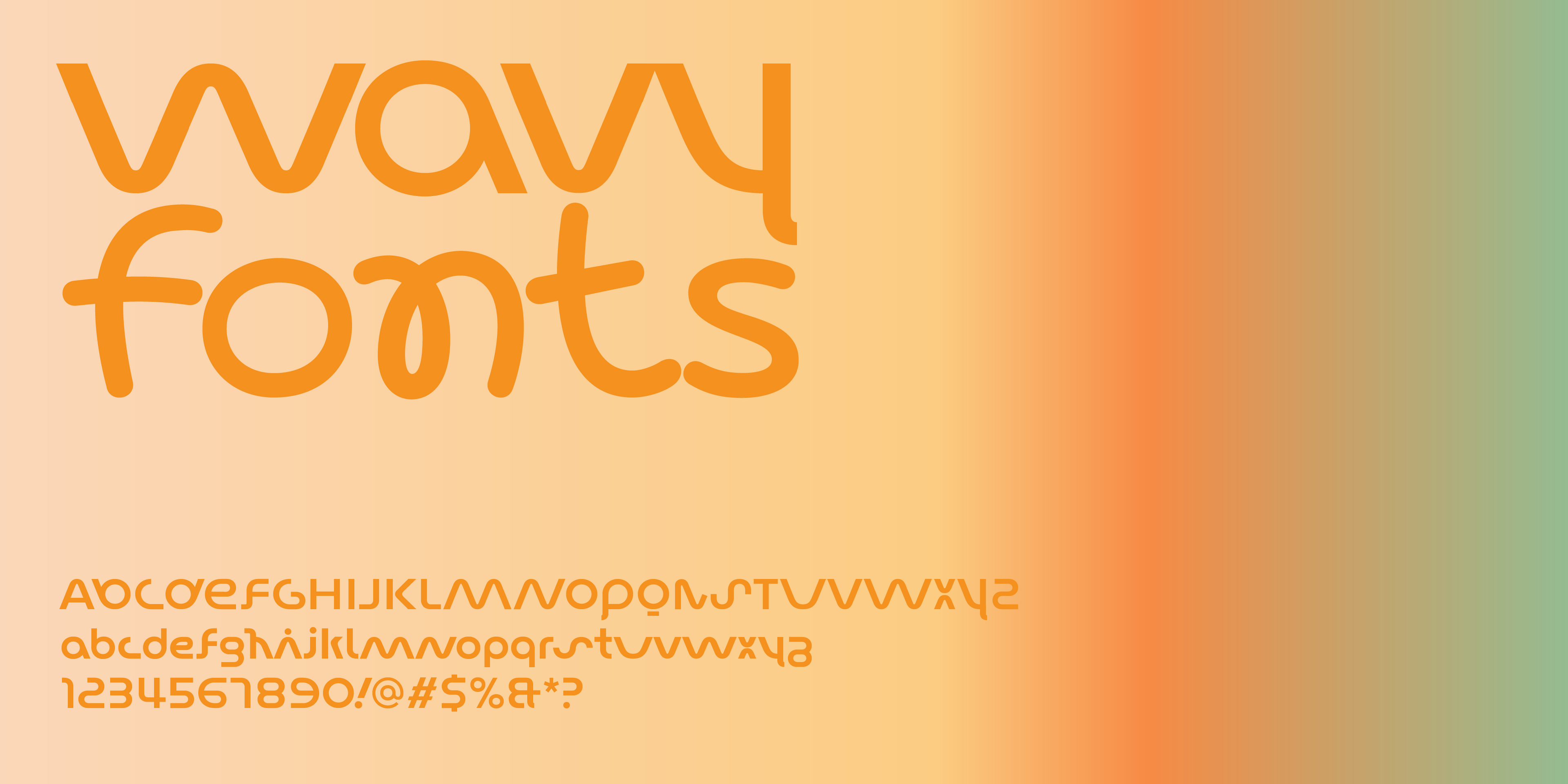
Las fuentes onduladas aportan una personalidad divertida a los diseños de logotipos y titulares. Ya sea que estés buscando una tipografía con un contorno ondulado general o una cuyas letras recreen un diseño similar a una onda de sonido, en este artículo, veremos ocho fuentes onduladas que aportan un carácter alegre y fresco a cualquier texto.
Tipografías divertidas y modernas
Esta primera tipografía, Lace Regular , es una fuente monolineal (los trazos tienen el mismo grosor) que se asemeja a una cuerda o cinta suave. Es una fuente agradable que se adapta perfectamente a los diseños de verano, con barras deformadas y terminales ondeando con el viento (compare el trazo horizontal de la letra f y el terminal de la letra r).
Skay, en grosores muy llamativos como Black, es una fuente ideal para logotipos con estilo. Skims utiliza una fuente similar , aunque su objetivo de comunicación es presumiblemente algo así como "formas corporales más suaves y redondeadas". Combinada con una paleta de colores cálida y apagada, crea un aspecto retro a través de su diseño de pincel suave y fluido. La tipografía se siente suave y burbujeante debido a su redondez hinchada, dinámica debido a sus ejes de letras irregulares y adaptable a cualquier espacio debido a su variabilidad de trazos de letras.
Kijs es una de mis fuentes favoritas para usar en estos días debido a su versatilidad. Esta fuente viene con letras alternativas que son más "estilo pincel" y, además, con glifos serif regulares que puedes intercambiar con los valores predeterminados más orgánicos. Si bien puede que no tenga un diseño de tipografía ondulada innata, configurar el texto en Kijs Bold (o más negrita) crea una apariencia natural y curva. La razón de eso es que algunas de las letras están en cursiva y otras letras están diseñadas en un estilo de pincel orgánico; compare las letras B y R y el ampersand también.
Si bien Pout puede no ser tan versátil como Kijs y otras fuentes onduladas, la tipografía tiene el poder de hacer que sus diseños de exhibición, como logotipos y titulares, se vean únicos. La tipografía obtiene su aspecto caprichoso al ser una fuente de contraste inverso donde los trazos horizontales son más gruesos que los trazos verticales. Esta fuente de exhibición también tiene muchos conjuntos estilísticos que le permiten elegir entre varios glifos, por ejemplo, una r o una w más curvas.
Fuentes modulares clásicas, curvas y redondeadas
Bauhaus Bau es una fuente clásica para un estilo retro que también es fácil de combinar. Aquí se muestra en ExtraLight y Bold. Le daría a esta tipografía una clasificación más de fuente curva debido a sus trazos rectos pero que carecen de una extensión de altura x. Aún así, dependiendo de las letras que uses para tu diseño, esta tipografía también creará una forma ondulada de cualquier texto.
La tipografía Vole requiere aplicaciones particulares, como un logotipo divertido, pero el aspecto poco común de sus barras internas onduladas hace que esta fuente sea una opción fácil de considerar. Los pesos más audaces de Vole crean un diseño fluido y muy curvo, especialmente cuando el espaciado entre las letras es ajustado.
Lace Rounded es la versión redondeada de “Lace” mencionada anteriormente, lo que le da a este tipo de letra un aspecto un poco más amigable. Me gusta que esté en mayúsculas y con un grosor de fuente más fino; se ve moderno y simple, pero personal. Lace Rounded tiene un contorno suave, lo que lo hace perfecto para proyectos de Cricut.
Sway Display es una nueva tipografía monolineal : todos los trazos en ángulo tienen una inclinación de +/-22,5 grados, lo que la hace perfecta para logotipos ondulados y textos de titulares. Sway tiene una estructura geométrica y una apariencia futurista. Funciona bien para industrias relacionadas con el sonido y objetivos de comunicación. Muchas letras tienen diseños de letras alternativos adicionales; muchos trazos se pueden conectar para crear un diseño de texto de una sola línea. Según los glifos utilizados, Sway puede crear un aspecto retro-moderno o hipster-contemporáneo.